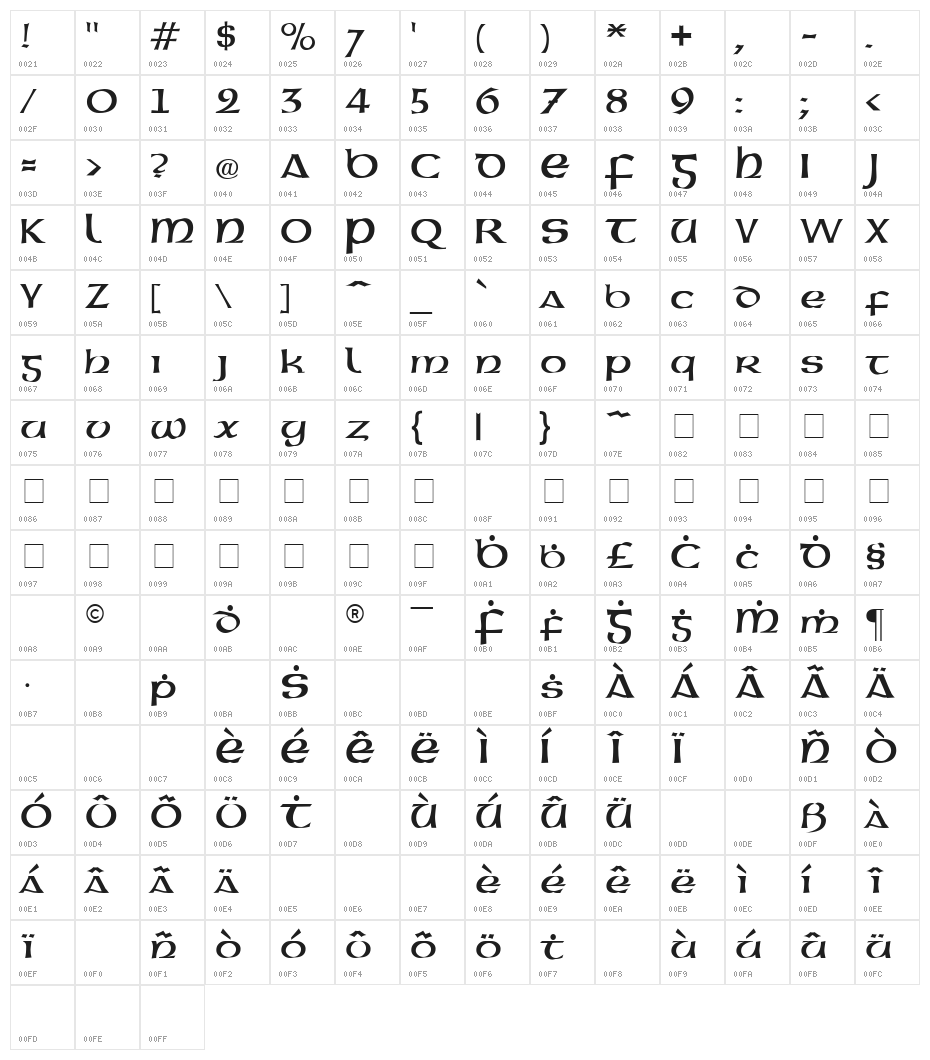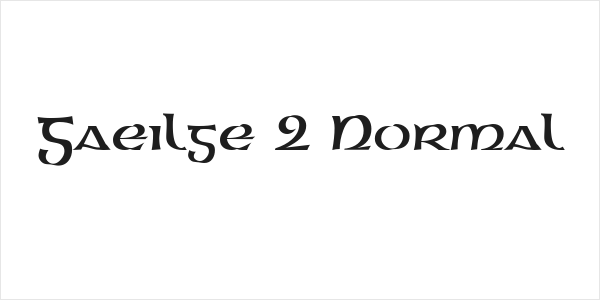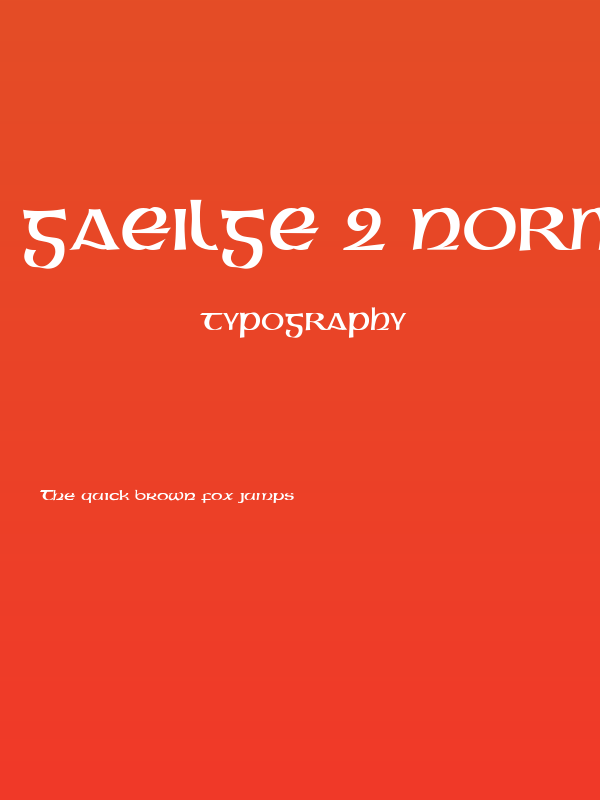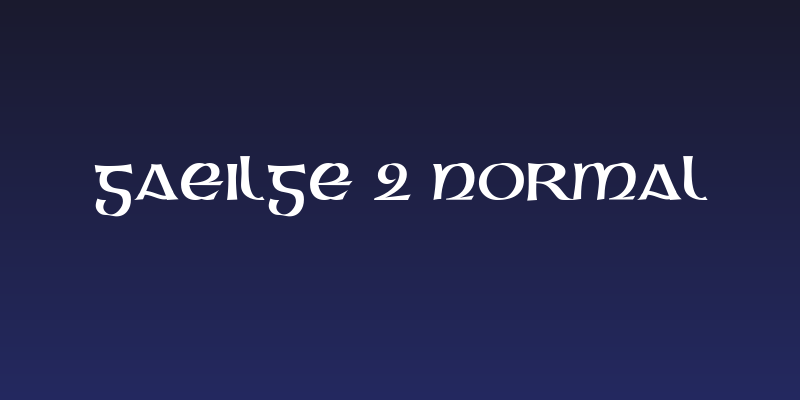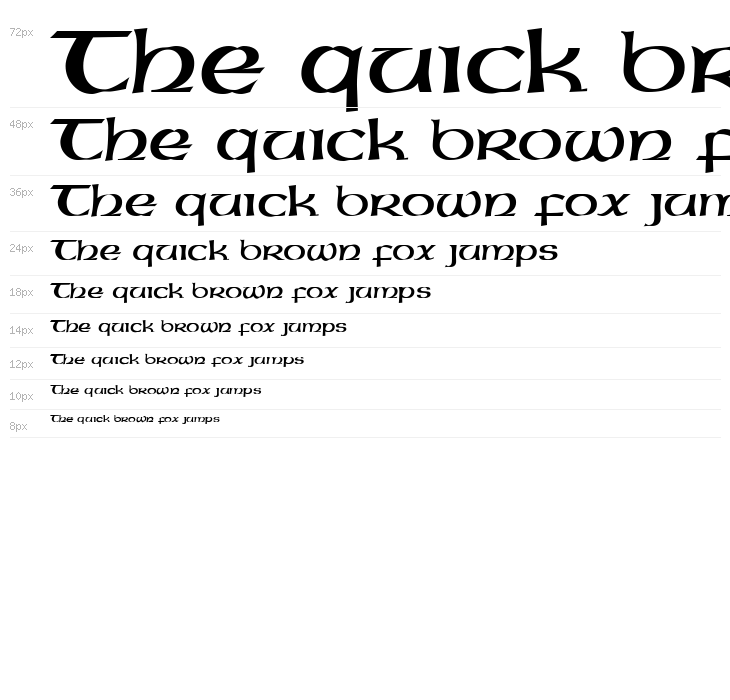
Gaeilge 2 Normal Font
| Vorgeschlagene Projekte | Ideal for projects that require a Celtic or historical theme, such as event invitations, themed posters, or branding for cultural events. |